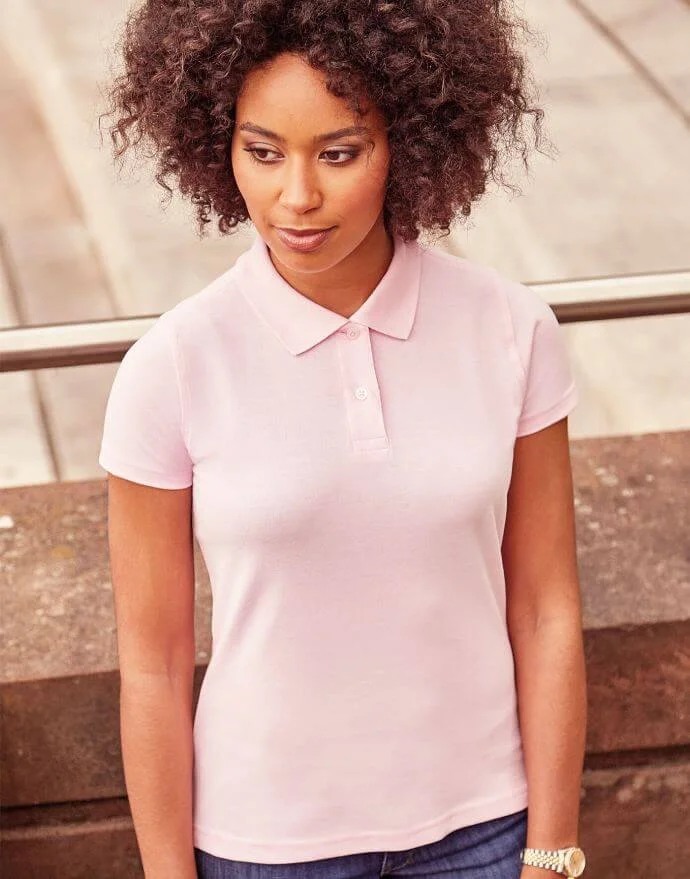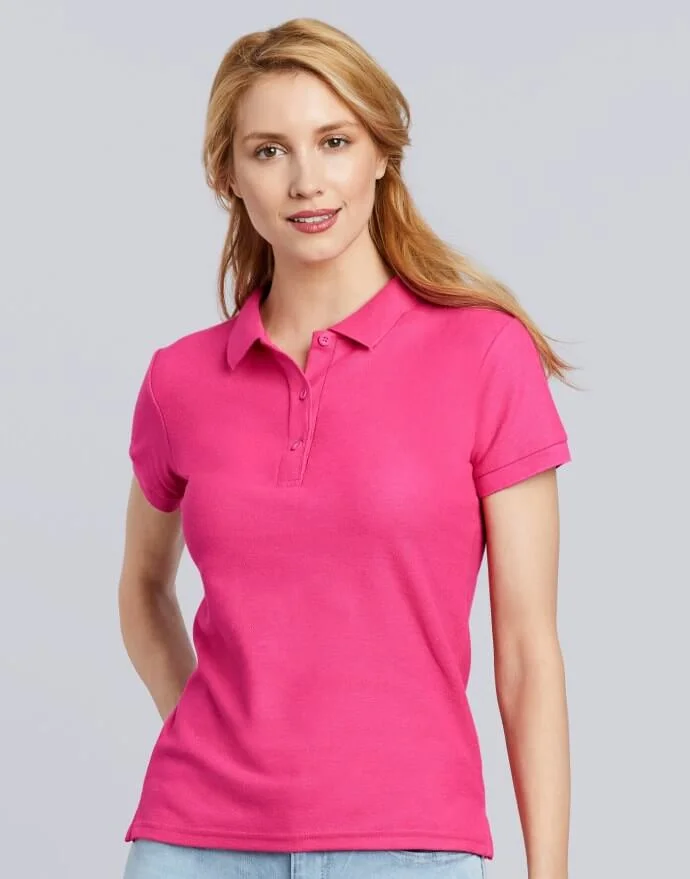
Polo donna rosa personalizzata? Colori e font per una stampa perfetta
I nostri consigli per stampare sul rosa senza perdere in leggibilità
Se stai pensando di acquistare una polo rosa donna personalizzata hai trovato la pagina che fa per te! In questo articolo troverai i nostri consigli su come realizzarla.
La polo è un indumento molto comodo per le mezze stagioni in particolare, essendo tendenzialmente realizzate in piqué, un tessuto realizzato con il cotone trapuntato, ovvero cucito a più strati.
Il risultato è un indumento ben traspirante e fresco, morbido al tatto e dall’aspetto elegante ma informale: la polo è la regina del business casual, adeguato per occasioni sportive, lavorative non troppo formali e ricreative.
L’abbigliamento personalizzato è molto in voga di questi tempi e sempre più persone scelgono un capo customizzabile rispetto ad un indumento griffato.
Ci sono però delle piccole regole basilare di cui dovresti tenere conto (per poi eventualmente ignorarle e lavorare di creatività): andiamo a vederle nel dettaglio.
Come scegliere la tipologia della stampa
Per quanto riguarda le polo potrai scegliere fra tre opzioni:
• Serigrafia
• Stampa digitale diretta
• Ricamo
La serigrafia è l’opzione più economica ed ha una ottima resa per i colori: consiste nell’applicazione a caldo della stampa desiderata tramite delle termopresse che la fondono sul tessuto, rendendola resistente ai lavaggi.
È particolarmente indicata per la stampa di molti pezzi per via del costo inferiore alla digitale diretta ma prevede un tempo maggiore per la realizzazione del telaio di stampa iniziale (la matrice).
La stampa digitale diretta invece riprende quella che è la stampa classica: il macchinario a getto d’inchiostro serigrafico, per mezzo di aghi, “disegna” sul tessuto la stampa desiderata ad alta risoluzione.
Si tratta di una tecnica più moderna che porta alcuni vantaggi, tra cui la possibilità di stampare su tanti tipi di tessuto, la resistenza nel tempo e la morbidezza della stampa stessa.
Il ricamo invece è realizzato tramite filo da cucito per mezzo di una macchina ricamatrice professionale precisissima: l’effetto è molto elegante ma porta delle limitazione di colori (tre) e di grandezza (9cmx9cm).
In base alle tue esigenze potrai scegliere quale delle tre modalità preferisci: se vuoi stampare un singolo capo ti consigliamo la stampa digitale diretta o il ricamo, a seconda della personalizzazione che hai in mente.
Polo donna rosa: quali colori di stampa scegliere
Vuoi creare la tua polo donna rosa personalizzata? Vediamo quali colori è meglio scegliere per ottenere una stampa carina e ben leggibile.
Se hai deciso di optare per una scritta è bene che valuti attentamente il colore che hai in mente per la stampa: molte persone non pensano a questo fattore e si ritrovano con lettere illeggibili su petto o schiena.
A seconda della tonalità di rosa che sceglierai la questione potrebbe variare leggermente, ma in linea di massima dovrai andare su colori scuri (nero, grigio scuro, blu scuro) o ad alto contrasto (viola, verde scuro, rosso).
Il rosa come sfondo è abbastanza neutro, non inficia particolarmente la leggibilità delle parole tranne nei casi in cui si scelga un colore poco contrastante, come il bianco, il salmone, il beige o simili.
Se ti vuoi divertire, sul web troverai molte tabelle di abbinamento (o contrasto) dei colori, qualora volessi realizzare una scritta che ne preveda più di uno: uno schema famoso è il cerchio di Itten per i contrasti.
Quali font scegliere per una polo donna rosa alla moda
Ci sono tre grandi categorie di font (caratteri grafici) tra cui puoi frugare per scegliere quello che più ti attira:
• Serif
• Sans serif
• Script
I Serif sono quei caratteri che presentano degli allungamenti alle estremità delle lettere, come quelli delle scritte lapidarie romane classcihe: sono più classici e danno un tono aulico alle parole.
I Sans Serif sono invece tutti quei font più moderni e lineari: trasmettono chiarezza e pulizia delle parole. Gli Script invece imitano la scrittura corsiva artigianale realizzata a mano: sinuosi e tondeggianti.
La legibility (leggibilità di un carattere) è una cosa oggettiva e non personale: gli Script sono utilizzati per testi brevi perché attirano l’occhio ma sarebbero per esempio faticosi per la lettura di un libro.
Il consiglio che ti diamo è quello di scegliere un font che abbia adeguate spaziature tra le lettere (non troppo appiccicate tra loro) e che abbia un alto rapporto tra l’occhio e il corpo totale dei caratteri.
Cosa significa? Stiamo parlando di quei font (come il Verdana) che presentano una ampia differenza tra l’altezza delle lettere basse (come a, x, c) e quella delle lettere alte (come l, t, h).
Se vuoi che la tua scritta sia chiara e concisa opta per caratteri grafici con forme convenzionali, come può essere il Minion Pro, se invece vuoi stampare una sola parola puoi lanciarti anche su un Comic Sans.
Insomma, come avrai potuto vedere la scelta finale per la tua polo donna rosa personalizzata la lasciamo a te ma ora hai tutti gli strumenti che ti servono per fare una valutazione consapevole.